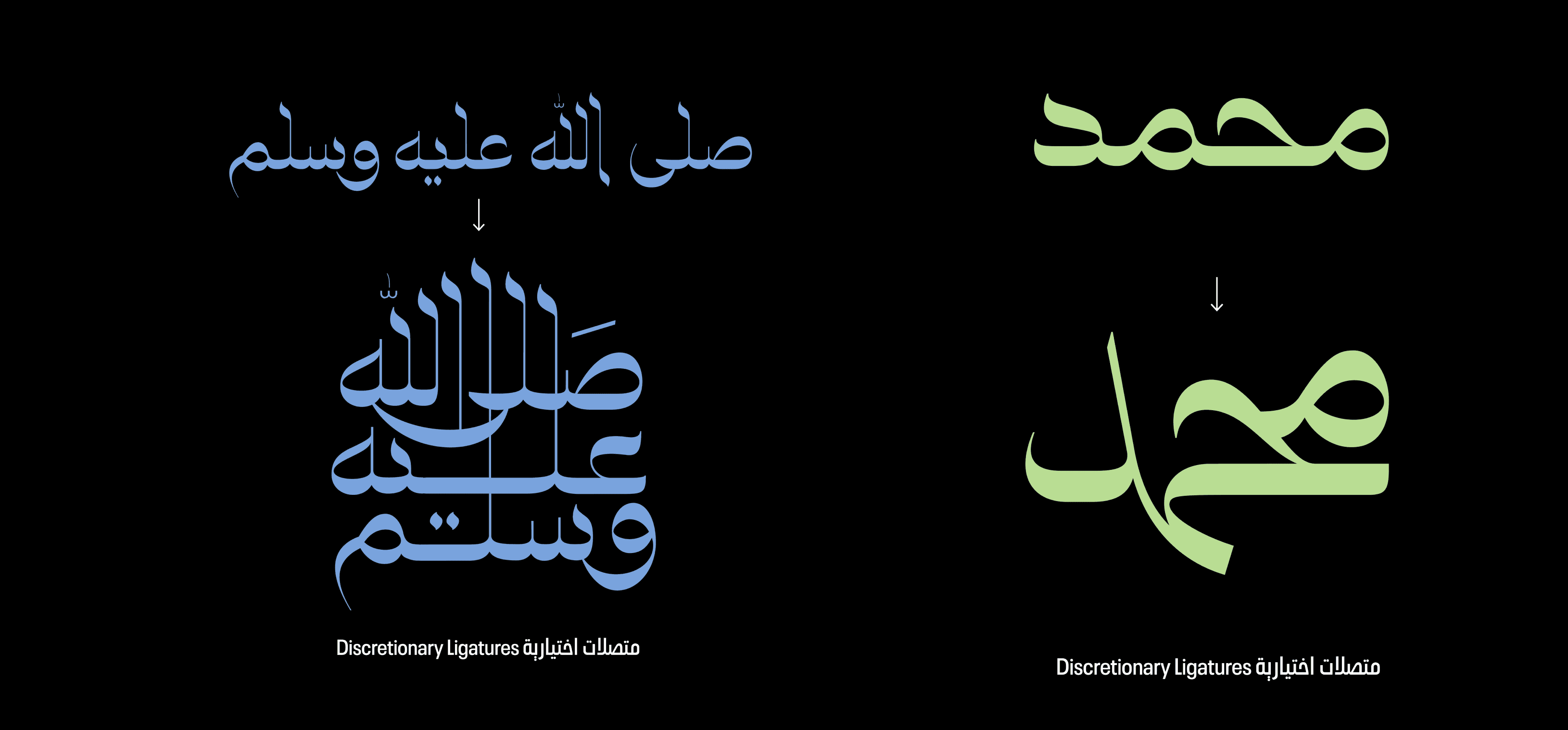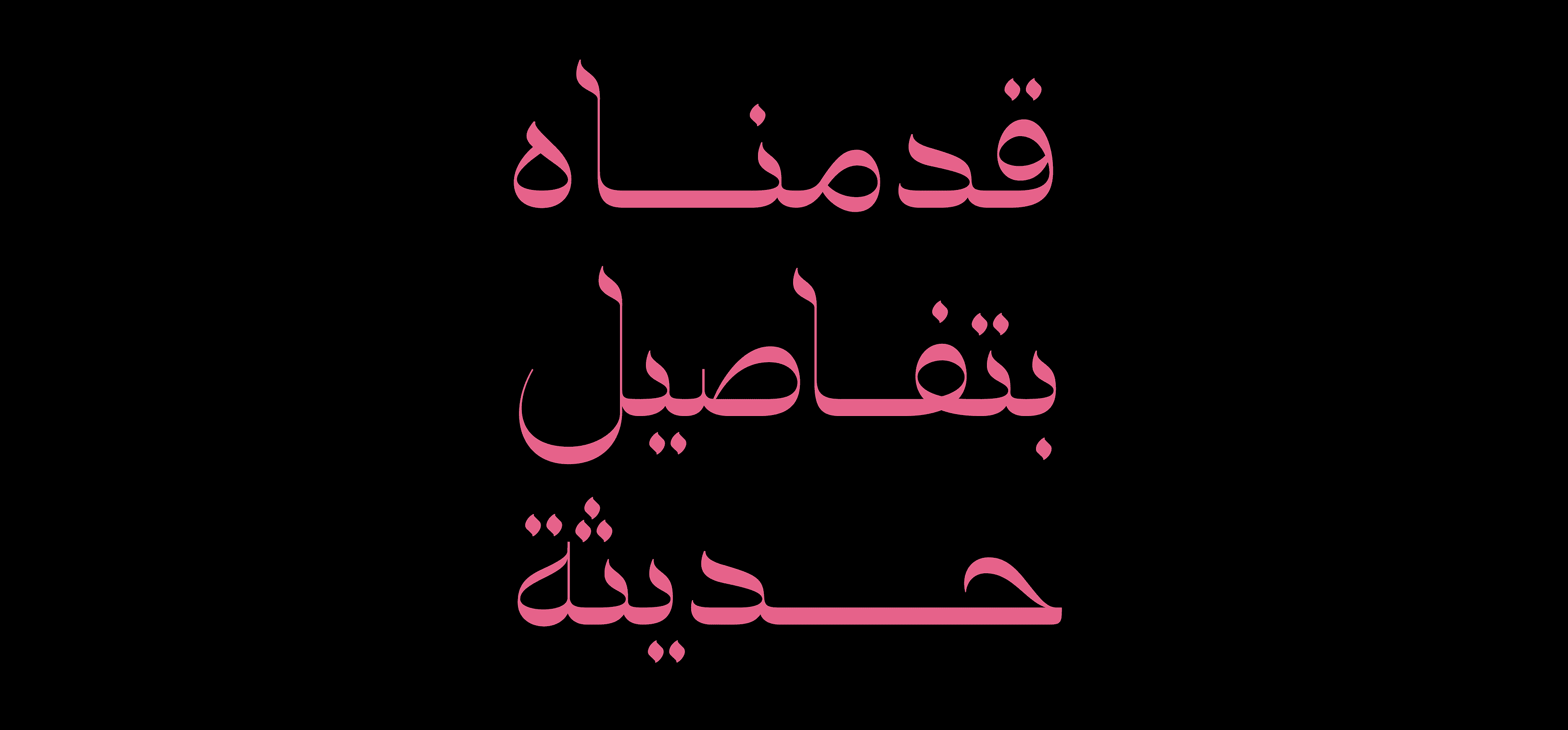
خط كوفي نيْسابوري – من Hadi Typefoundry
خط عرض جريء وأنيق صُمم خصيصًا للعناوين القوية والملصقات ذات التأثير البصري العالي، مستوحى من الخط الكوفي النيسابوري الكلاسيكي.
يهدف هذا الخط إلى تقليل المساحات البيضاء الزائدة وخلق كتل نصية محكمة ومتماسكة، من خلال قلب التباين وتوزيع الوزن في أعلى وأسفل الحروف (الطُّرُوَز).
يبدأ التصميم من بنية الحرف الأساسية، مما ينتج عنه أسلوب بصري فريد يوازن بين التراث والحداثة، ويمنح المشاريع التحريرية والطباعية حضورًا مميزًا ولافتًا.